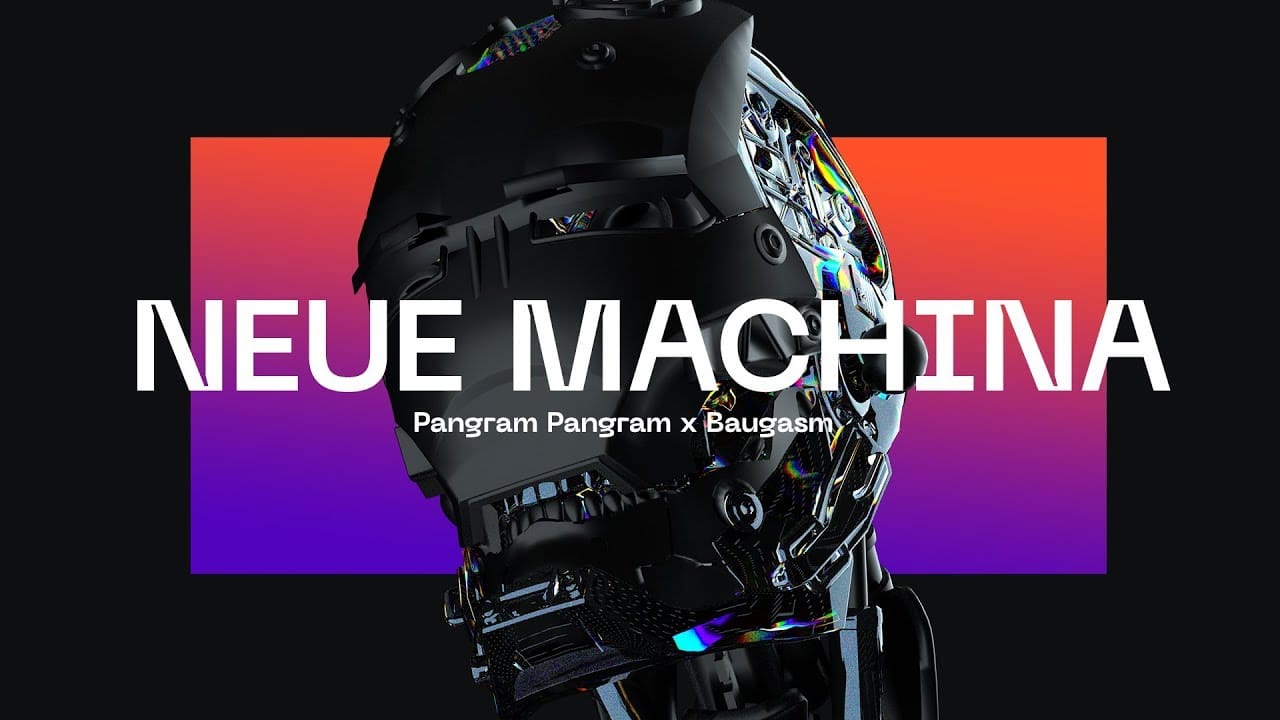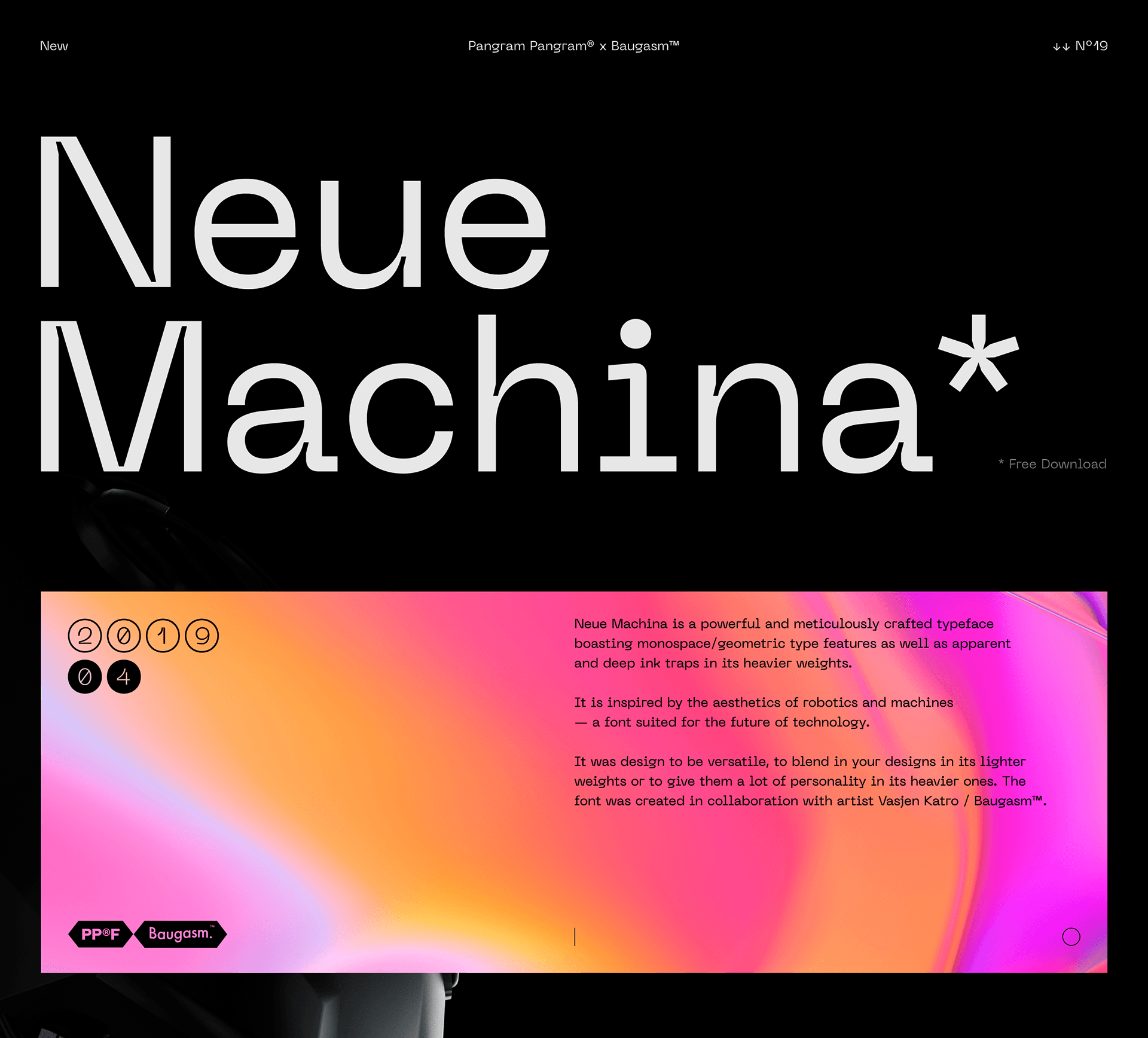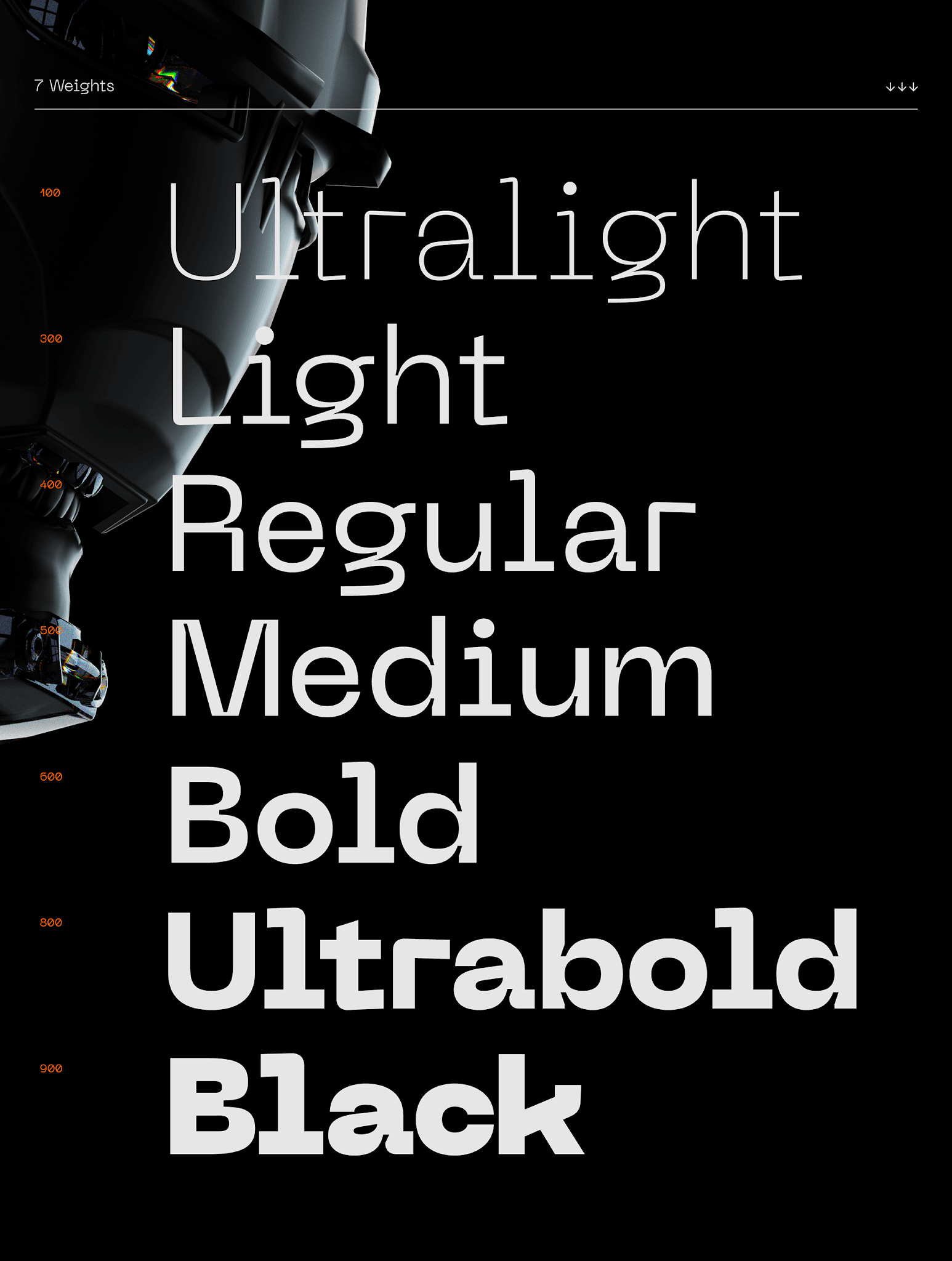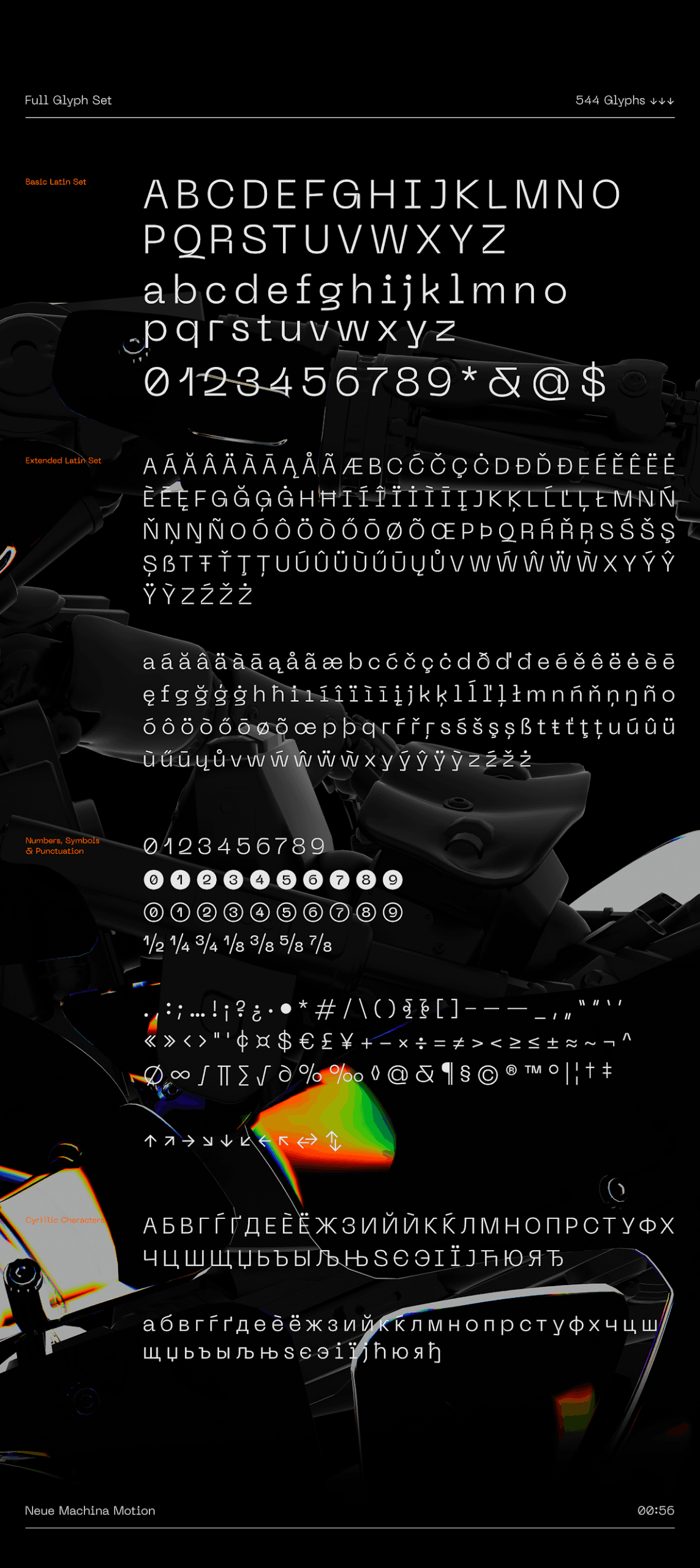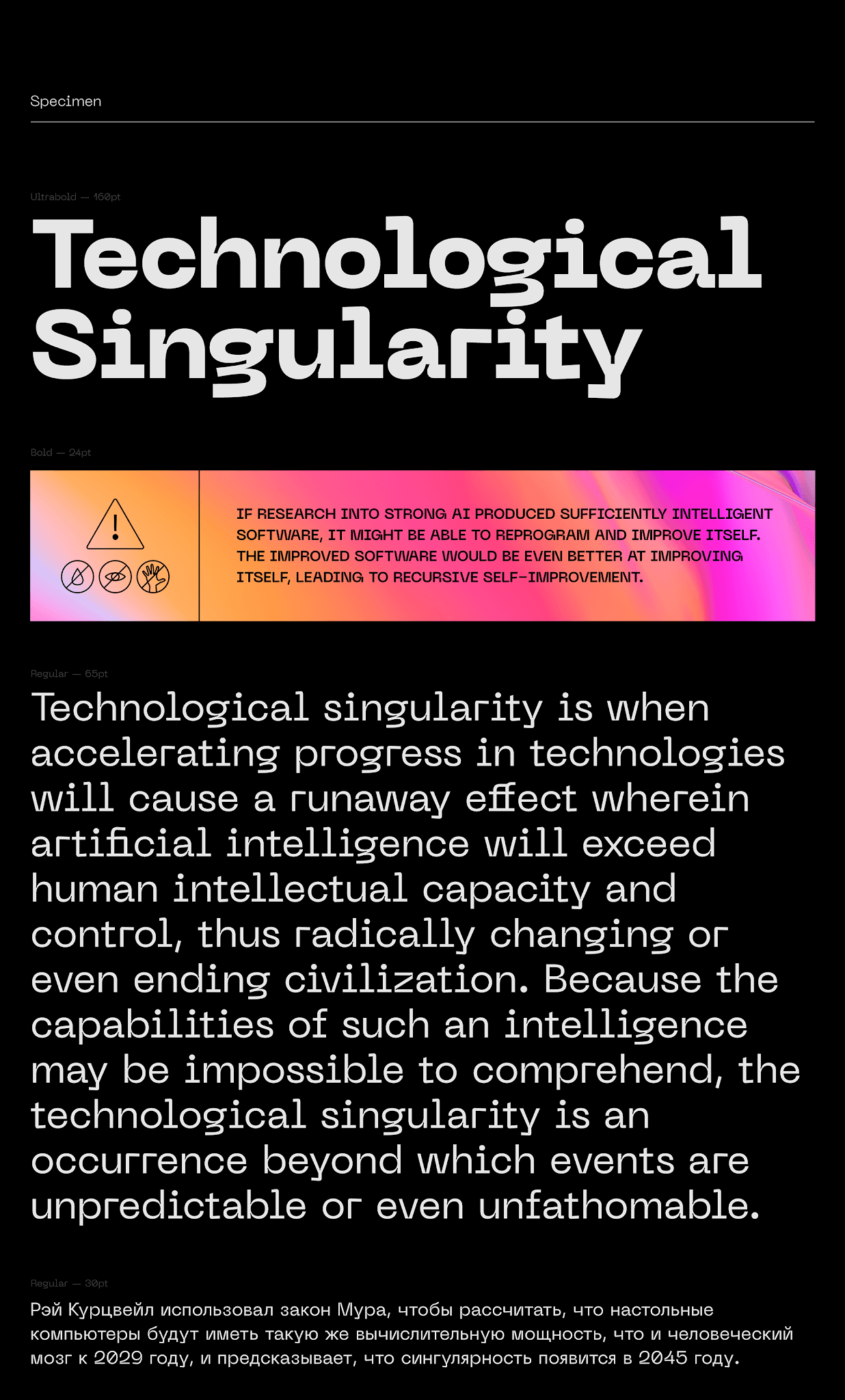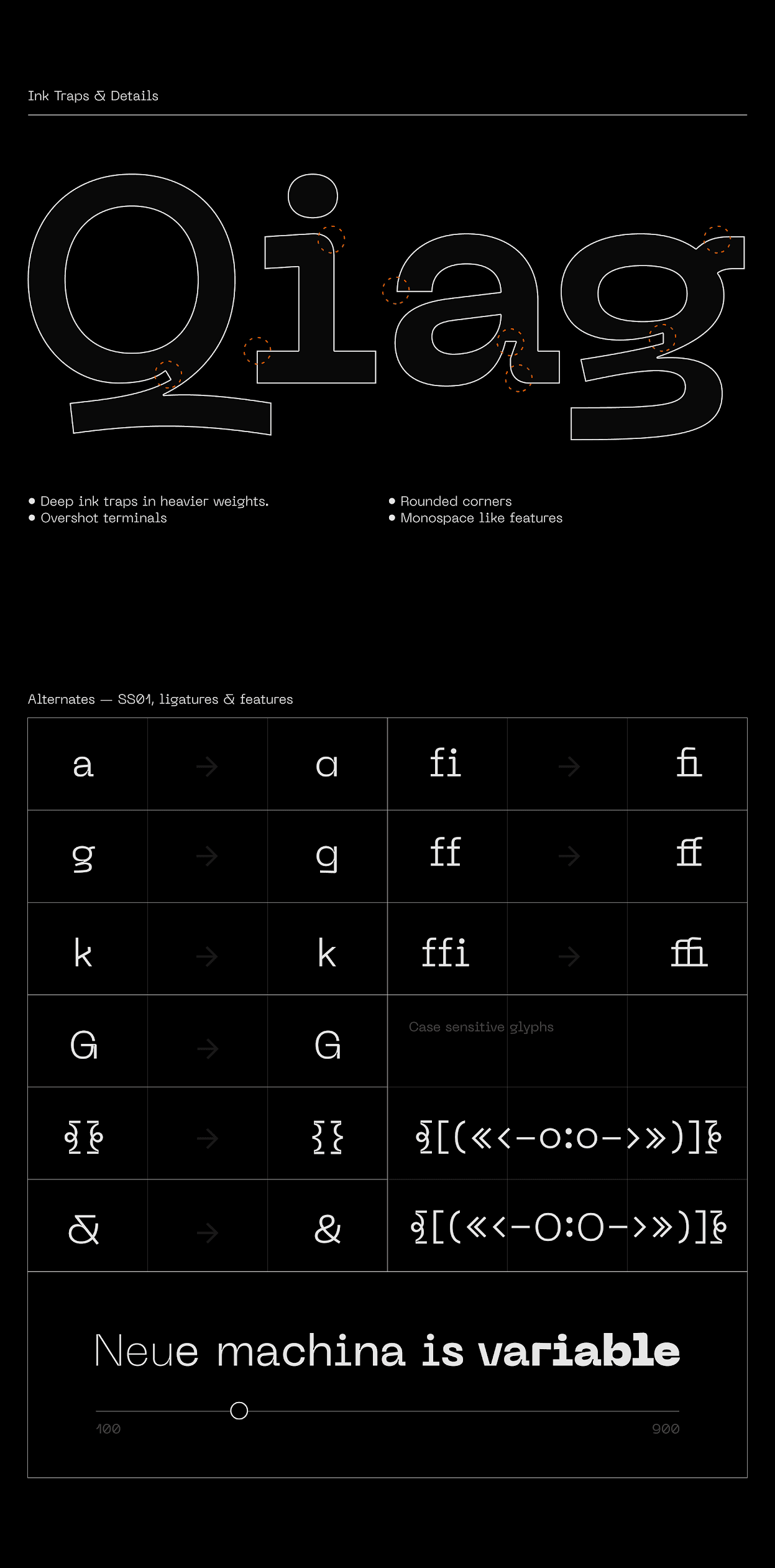
Neue Machina là một kiểu chữ mạnh mẽ và được chế tác tỉ mỉ với các tính năng của kiểu hình học / không gian đơn cũng như các bẫy mực sâu và rõ ràng với trọng lượng nặng hơn. Nó được lấy cảm hứng từ tính thẩm mỹ của robot và máy móc – một font chữ phù hợp với tương lai của công nghệ.
Đó là thiết kế để trở nên linh hoạt, để pha trộn các thiết kế của bạn với trọng lượng nhẹ hơn hoặc tạo cho chúng nhiều cá tính trong những thiết kế nặng hơn của nó. Font chữ được tạo ra với sự hợp tác của nghệ sĩ Baugasm. Neue Machina Font Family bao gồm 7 weight với 544 glyphs mỗi cái kết hợp với Stylistic Alternates, chữ ghép và hơn thế nữa. Hỗ trợ ngôn ngữ cho Châu Mỹ, hầu hết Châu Âu và các ngôn ngữ Kirin. Thiết kế bởi Mat Desjardins.